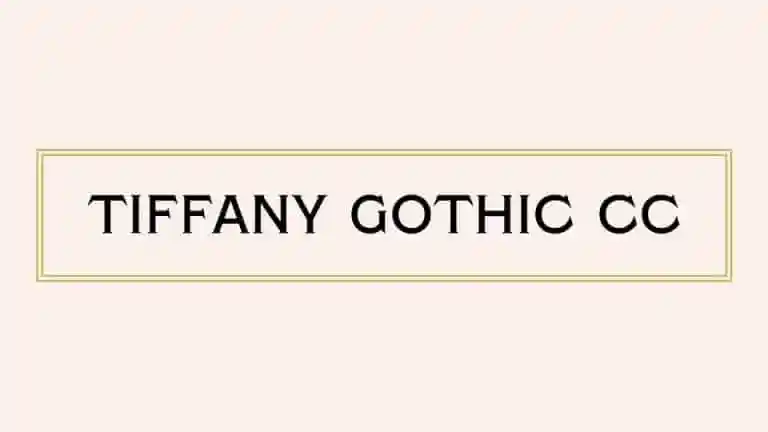
Tiffany Gothic CC Serif Font – Download Grátis
Tiffany Gothic CC Serif Font é uma fonte serif geometrica que inspira-se nos traços modernistas encontrados em planilhas arquitetônicas contemporâneas. Revivida pelo American Type Founders como Tiffany Gothic em 1901, esta fonte provavelmente tem suas origens no final do século XIX. Em 1912, ATF mudou o nome para Typo Gothic, e desde então as letras desapareceram da cena. Ao contrário de seu famoso parente, Copperplate Gothic, Tiffany não ostenta a popularidade nem o prestígio que este carrega. Na verdade, até agora, essa fonte ainda não teve uma versão digital. Tiffany Gothic CC oferece um toque distinto às suas linhas geometricas, combinando elementos modernos com uma arquitetura clássica, criando uma experiência visual única e interessante. Em um mundo de digitais e gráficos que tendem a simplificar o processo criativo, Tiffany Gothic CC traz uma paixão pelo detalhe e elegância. Seja em logotipos, títulos de página ou materiais publicitários, esta fonte exalará um toque sofisticado sem comprometer a eficácia do seu uso. Com sua presença sóbria e elegante, Tiffany Gothic CC será uma escolha acertada para aqueles que buscam um design gráfico único e arquiteturalmente sofisticado.